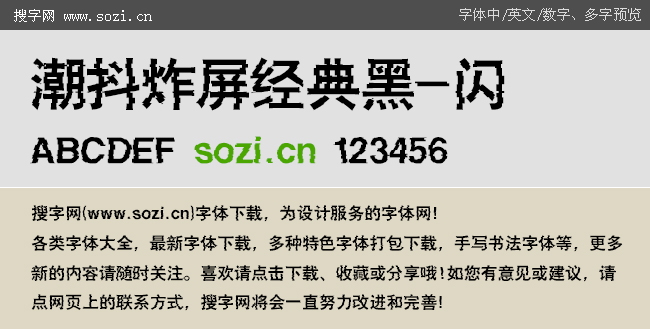
潮抖炸屏经典黑-闪
搜字网提供一款潮抖炸屏经典黑-闪中文字体下载,潮抖炸屏经典黑-闪是一款艺术黑体字体,潮抖炸屏经典黑以黑体字为基准,加入抖动笔画与切割错位效果,潮流动感,重新定义时尚字体。适合用于标题设计、海报设计、包装设计等场景广泛应用。(本字体为个人非商用版,商用请联系作者购买授权。官方网址:http://www.reeji.com 联系方式:021-58597892)